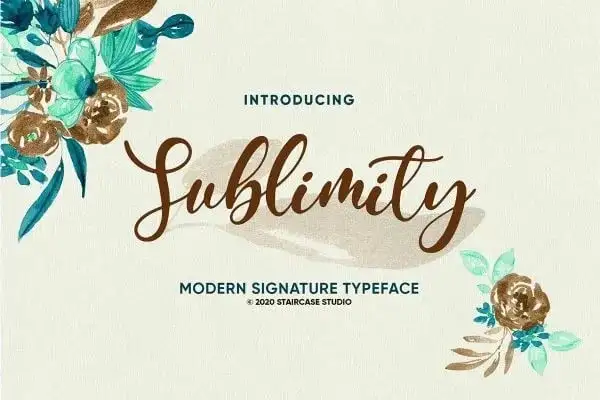
Sublimity Script Font – Fonte Grátis
Sublimity Script Font
Sublimity Script é uma fonte de script que foi feita à mão com a escrita natural do dedo humano. É impressionante ver como as linhas grossas e finas criam um belíssimo traçado de letra pela qual você pode escrever diretamente no seu teclado! Esta elegante fonte de calligrafia é perfeita para uma variedade de projetos, desde a criação de marcas, postais e cartões até trabalhos DIY com máquina cortadora. Ela também se destaca em artes decorativas em paredes, textos, embalagens, scrapbooking, cartas de cumprimento e muito mais! A Sublimity Script é uma fonte perfeita para qualquer projeto que busque elegância e sofisticação.